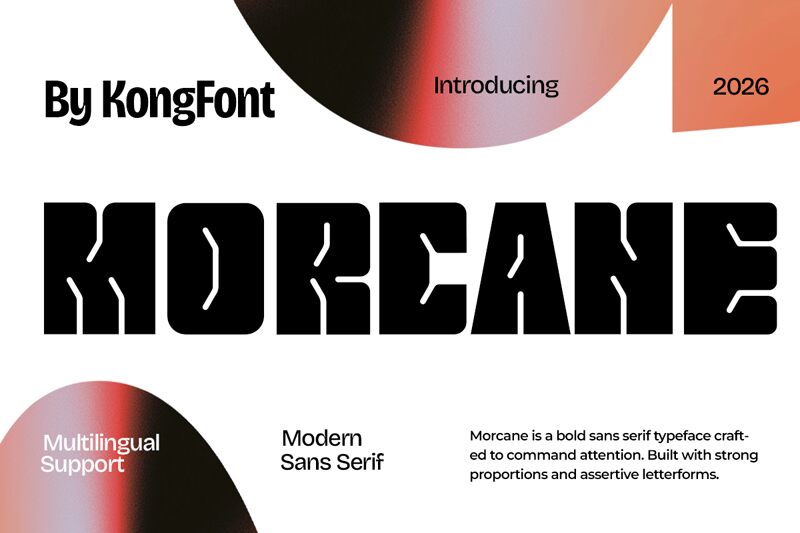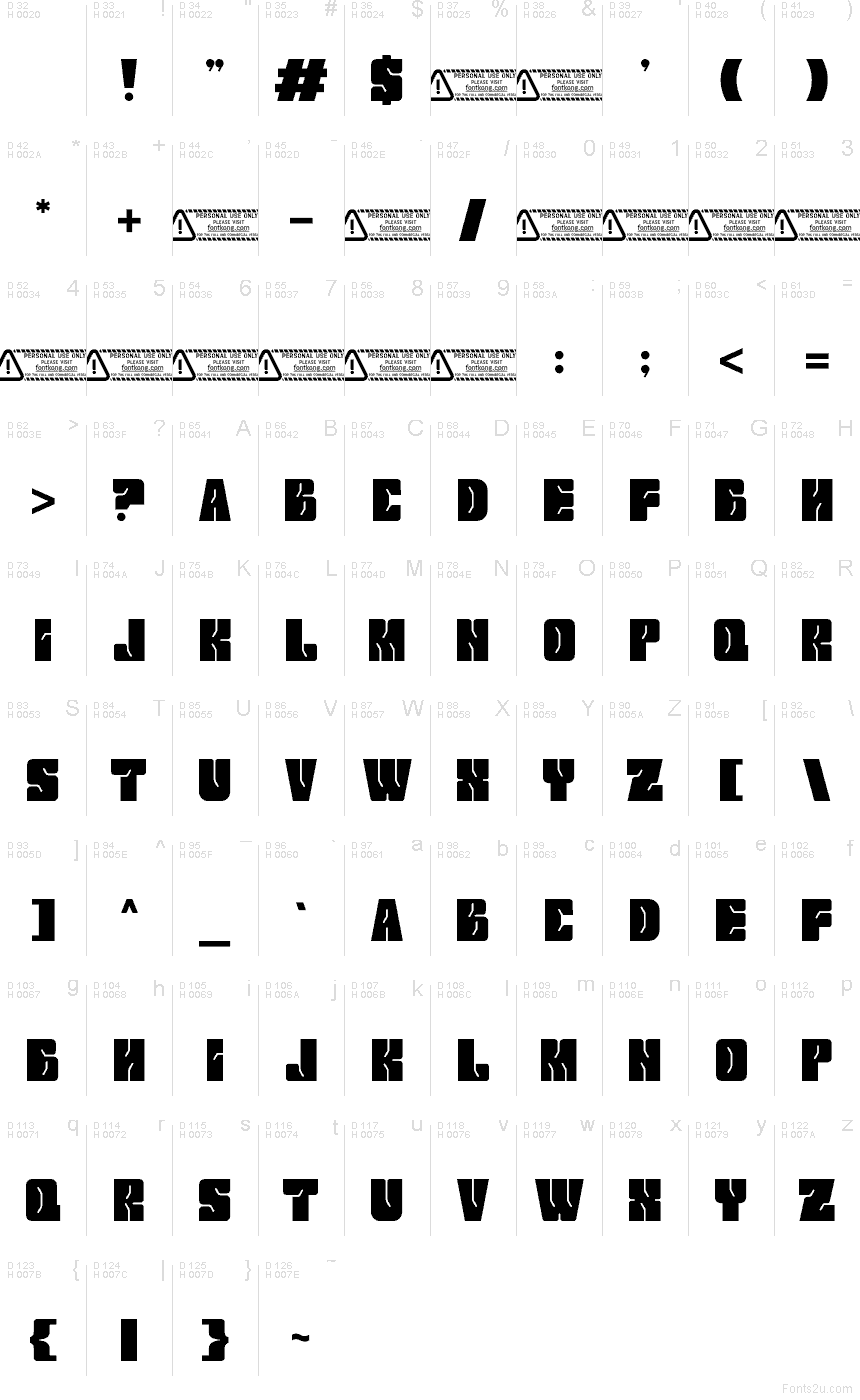
Morcane od Typeface (Kong Font) to nowoczesny, wycinany krój pisma typu display o wyrazistym, futurystycznym charakterze. Litery zbudowane są z ciężkich, czarnych bloków, przeciętych smukłymi białymi liniami i ostrymi nacięciami, dzięki czemu alfabet sprawia wrażenie wyrytego, a nie narysowanego, z rytmiczną ostrością powtarzającą się w każdym znaku.
To sprawia, że ten darmowy font świetnie sprawdza się w tytułach plakatów, okładkach albumów, brandingu odzieży streetwearowej, grafikach eventowych i planszach tytułowych, gdzie krótki napis potrzebuje odważnej, inżynieryjnej prezencji. Działa doskonale również w monogramach i krótkich nagłówkach, ponieważ wewnętrzne cięcia nadają nawet prostym grupom liter zakodowany, industrialny styl.